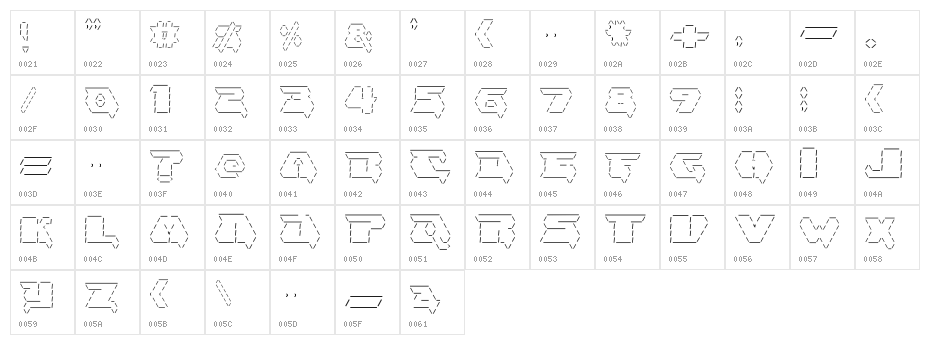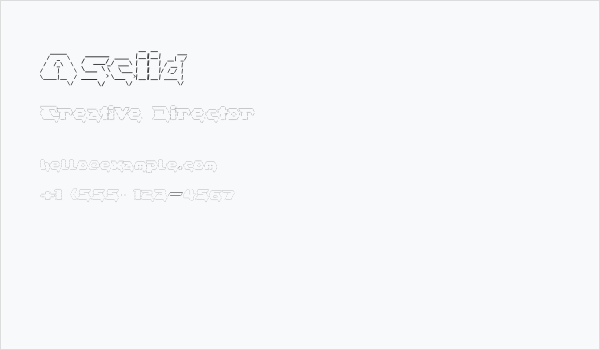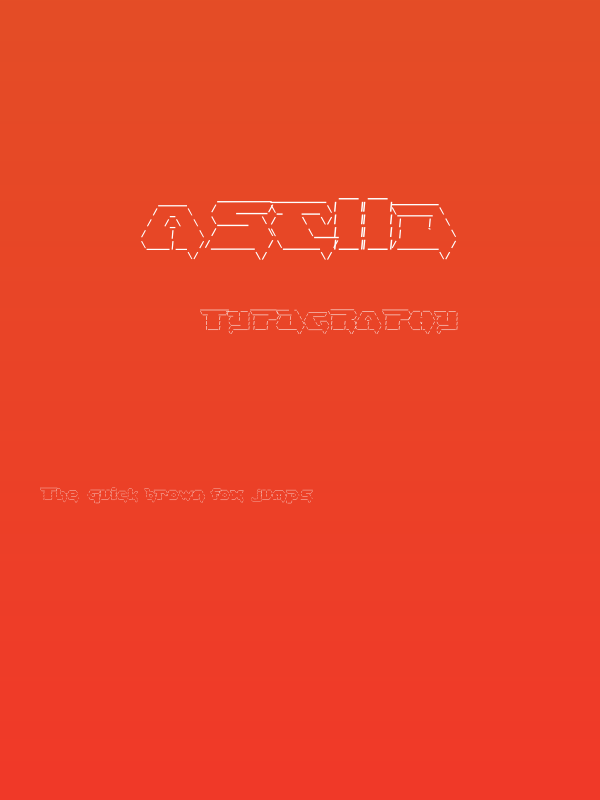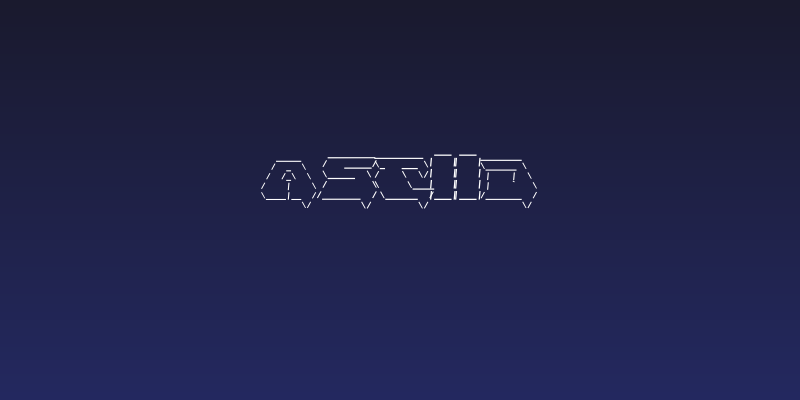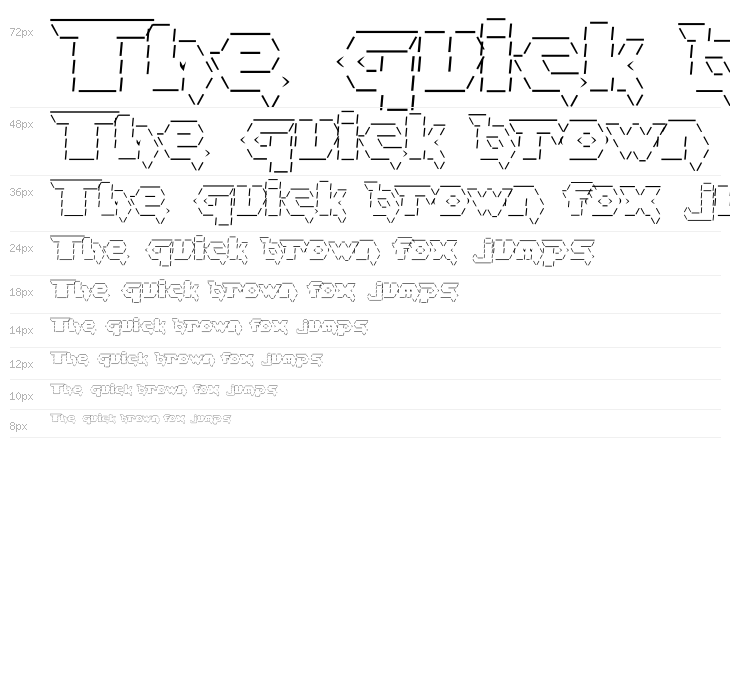
Asciid Font
| Stile generale | Futuristic, Digital |
| Caso d'uso | Logos, Posters, Digital Art |
| Progetti proposti | Ideal for digital art projects, tech-themed posters, or creative coding displays. |